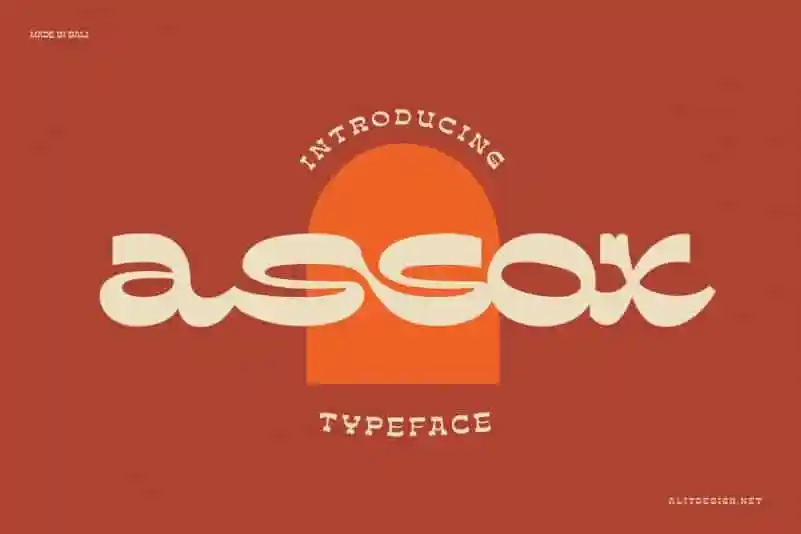
Assox Display Font – Download Grátis
A Assox Display Font é uma ótima escolha para aqueles que valorizam a combinação entre modernidade e nostalgia. Inspirada nos estilos vintage dos anos 70, essa fonte traz características divertidas e clássicas, sem parecer séria ou formal. Seu design foi criado por alit design, uma equipe de designers dedicados que buscam inovar com cada projeto. O que torna a Assox Display Font ainda mais especial é sua facilidade de memória: fácil de se lembrar e rápida para usar em projetos visuais diversos. Além disso, como menciona o designer original, essa fonte se destaca por suas qualidades estéticas únicas e valor próprio. Seja você um profissional de design ou alguém que aprecia recursos gráficos, a Assox Display Font é uma opção ideal para dar vida à sua arte visual. Seu estilo divertido e clássico a torna fácil de lembrar, mas ainda assim com personalidade e valor, garantindo um design único e memorável em seus projetos. Além disso, a Assox Display Font é uma ótima escolha para quem busca um toque vintage sem o excesso de formalidade. Traz consigo tanto diversão quanto elegância, tornando-a perfeita para criações que precisam ser lembradas e percebidas em primeiro lugar.